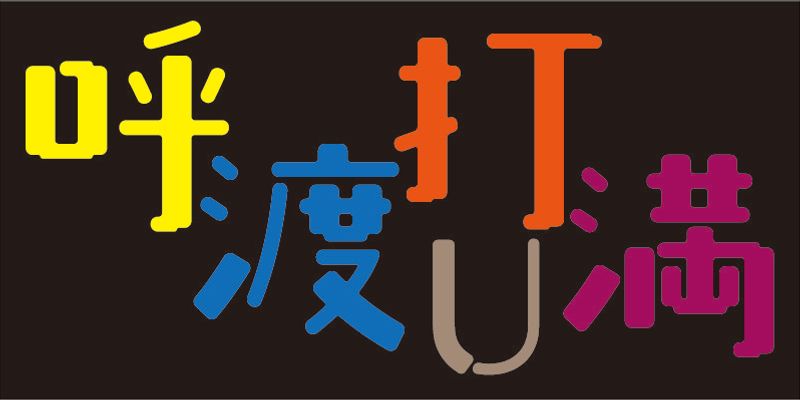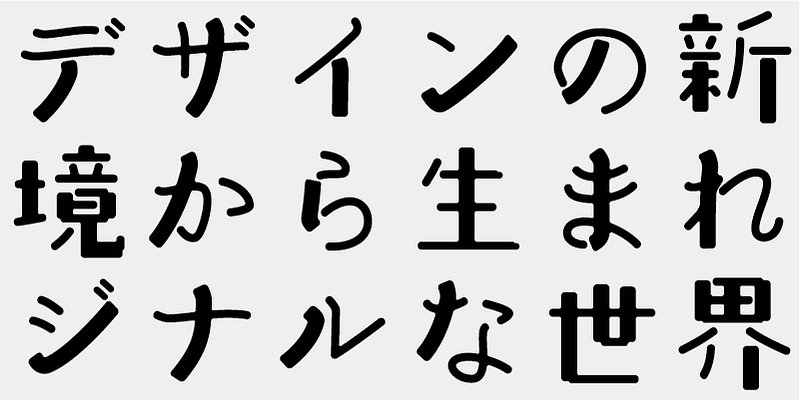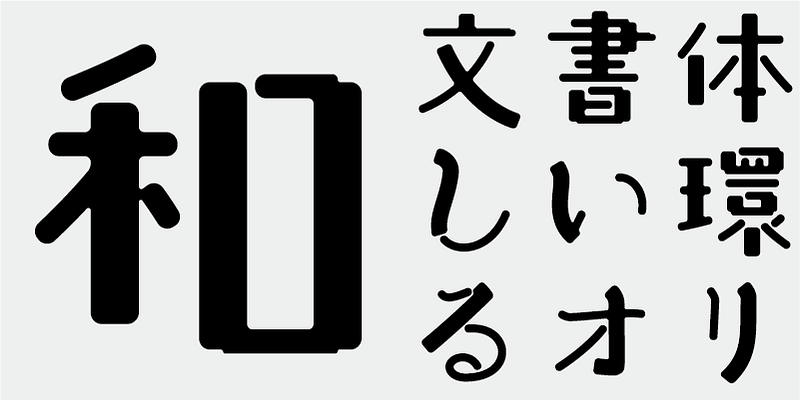
Dieses „einzigartige“ Gewicht U basiert auf dem Gewicht R, fügt aber einige dickere Elemente hinzu. Sie erzeugt unterschiedliche visuelle Effekte, je nachdem, wie Sie sie verwenden.
Diese Schrift enthält die 1.000 wichtigsten Kanji-Zeichen, die aus den Häufigkeitstabellen von Zeitungsunternehmen, Verlagen und linguistischen Forschungsinstituten ausgewählt wurden, sowie 206 Kana-Zeichen und Satzzeichen.
In der heutigen japanischen Schriftproduktion gelten die 7.000 Zeichen des JIS-Standards als unabdingbar. Aber brauchen alle Schriften wirklich 7.000 Zeichen? Im Zeitalter des Fotosatzes wurden weit weniger Zeichen benötigt. FONT1000, eine Gruppe unabhängiger Schriftdesigner, ging von dieser einfachen Frage aus. Wir haben die mindestens 1.000 (ideografischen) Kanji-Zeichen ausgewählt, die für den Satz in Japanisch erforderlich sind, und aktiv Schriften und Schriftbilder dafür entworfen. Dieser 1000-Kanji-Zeichensatz wurde unter Verwendung von Zeichenhäufigkeitsdaten ausgewählt, die u. a. von Zeitungsunternehmen, Verlagen und Sprachforschungsinstituten zusammengestellt wurden, und enthält auch Kana-Silbenzeichen und Satzzeichen. FONT1000 begann 2001 mit 25 Designern und 25 Schriften. Heute haben wir 130 Schriften und sind auf fast 40 Mitglieder angewachsen, sodass wir an Schriften mit mehr Zeichen arbeiten können.